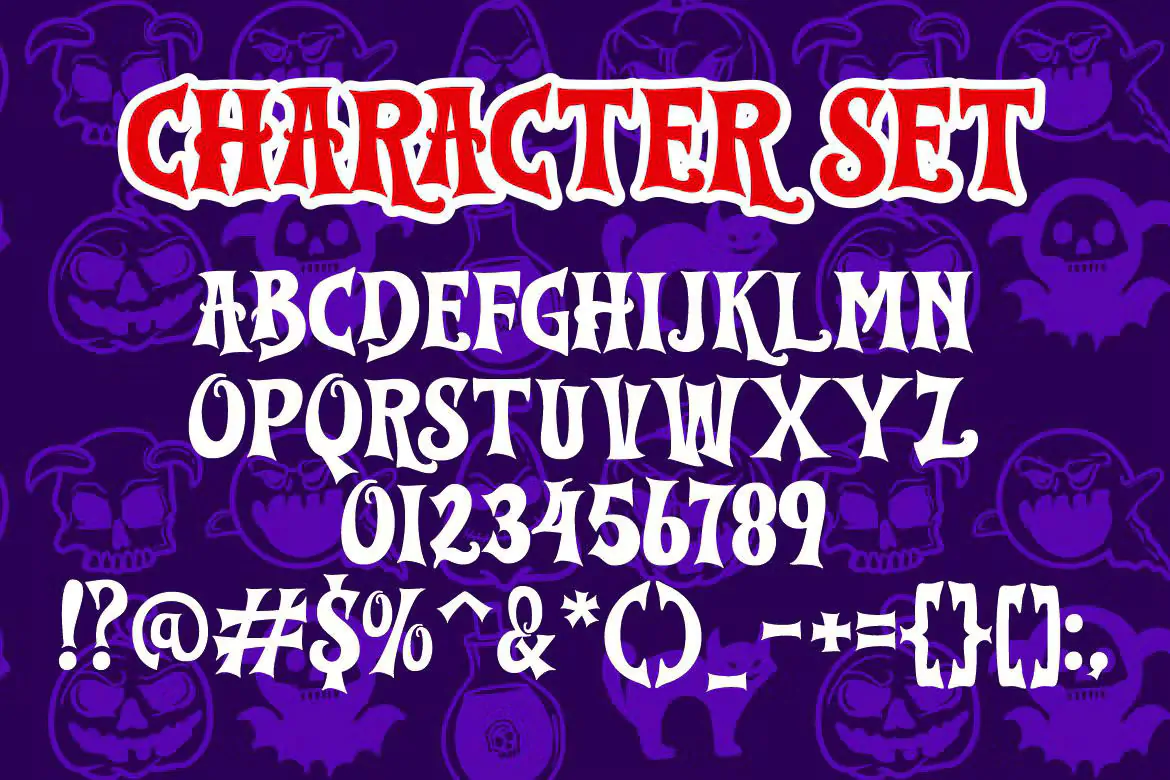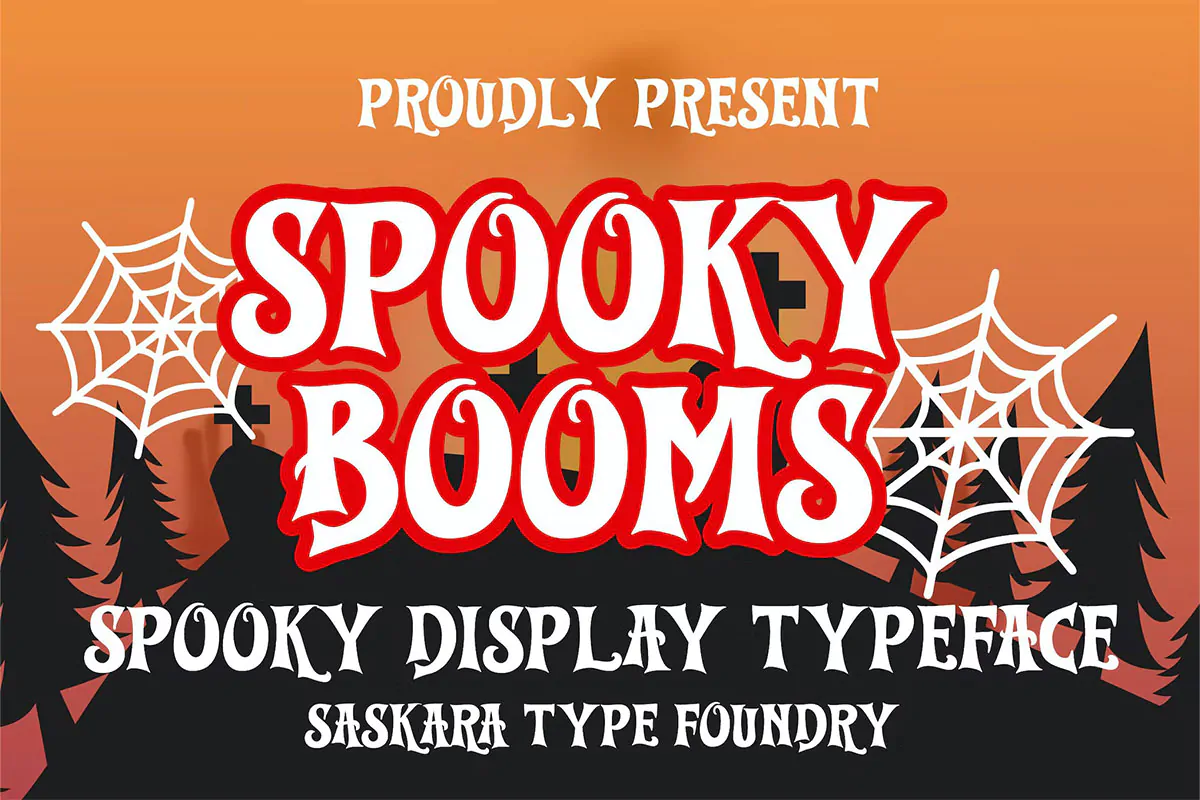
فونت جادویی و ترسناک Spooky Booms
فونت جادویی و ترسناک
فونت جادویی و ترسناک Spooky Booms یک قلم فوق العاده زیبای انگلیسی است که مناسب جهت استفاده در طراحی انواع پوستر، بنر، کارت تبریک، طرحهای هاووین و … میباشد.